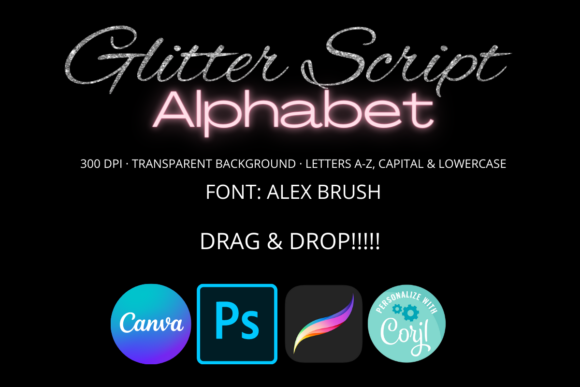
Silver Script Letters Clipart
Se você está procurando ativos de alta qualidade como Silver Script Letters Clipart, este pacote premium é uma escolha fantástica para seus projetos criativos.
Trabalhado com precisão, Silver Script Letters Clipart fornece vetores limpos, tipografia suave e uma licença comercial para sua tranquilidade.